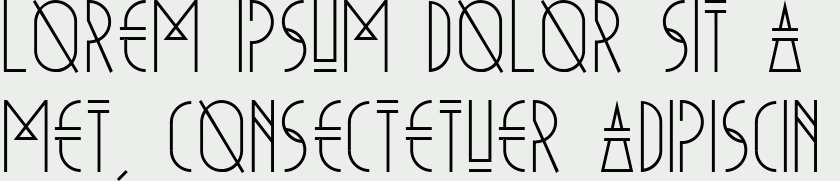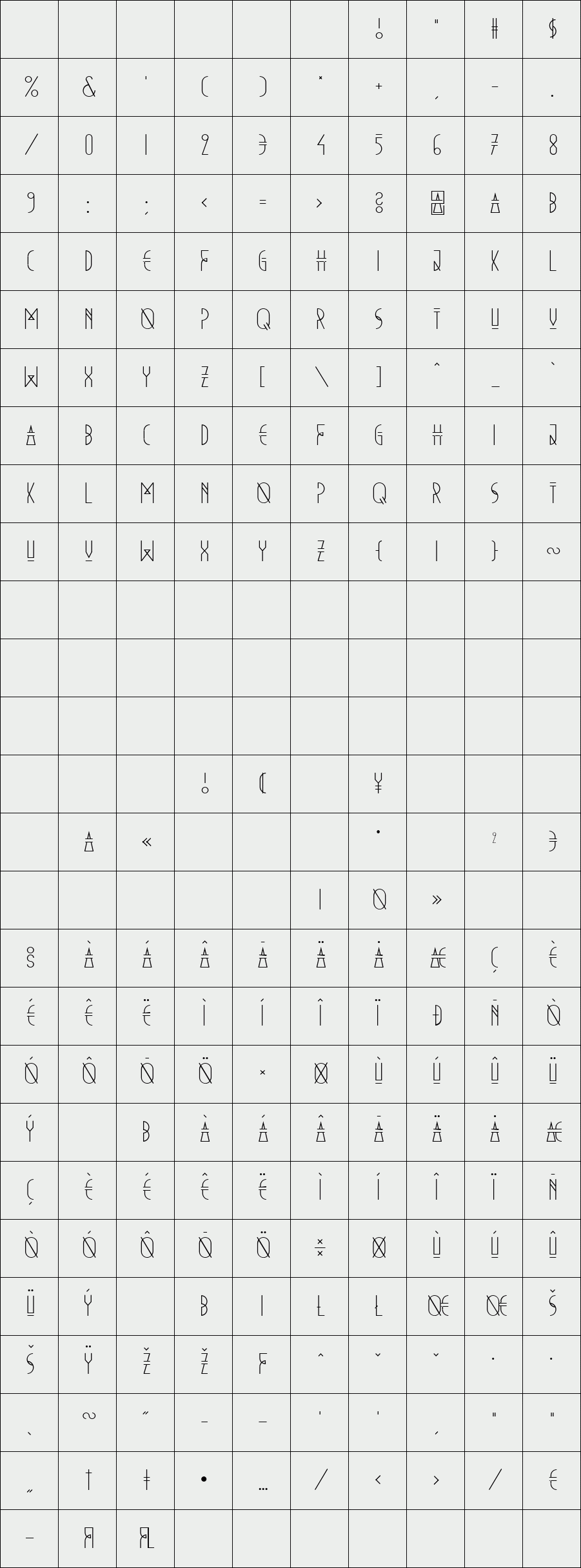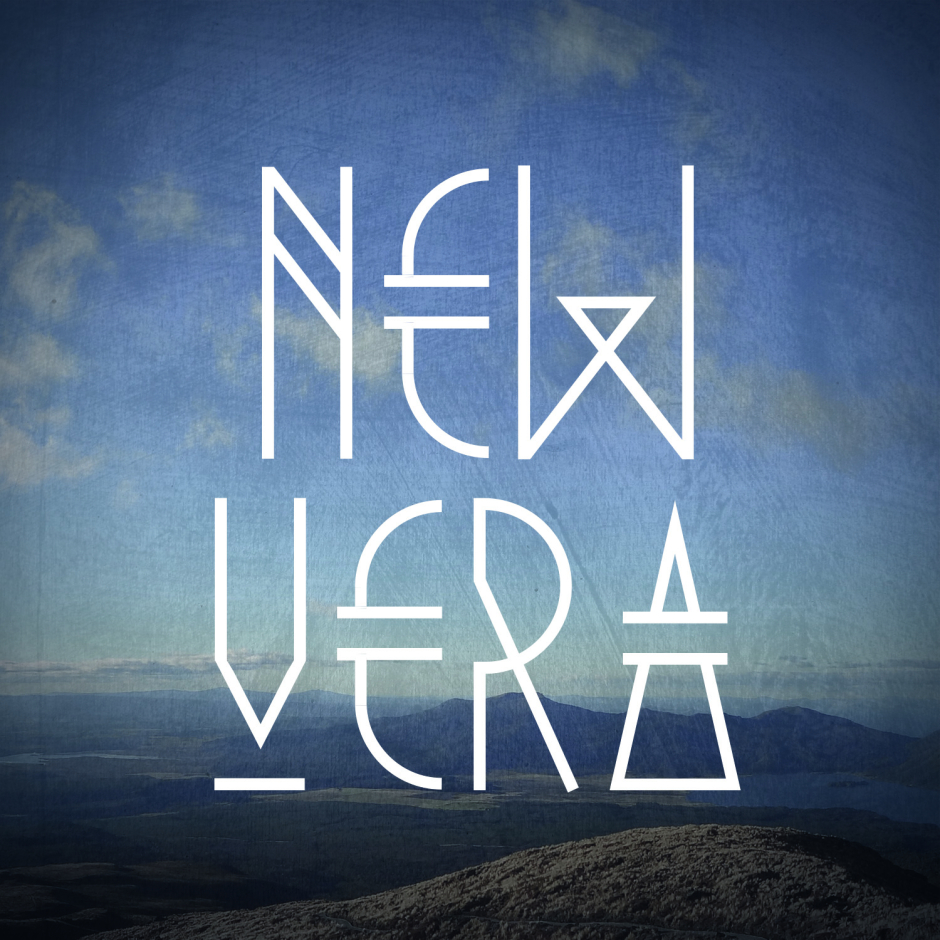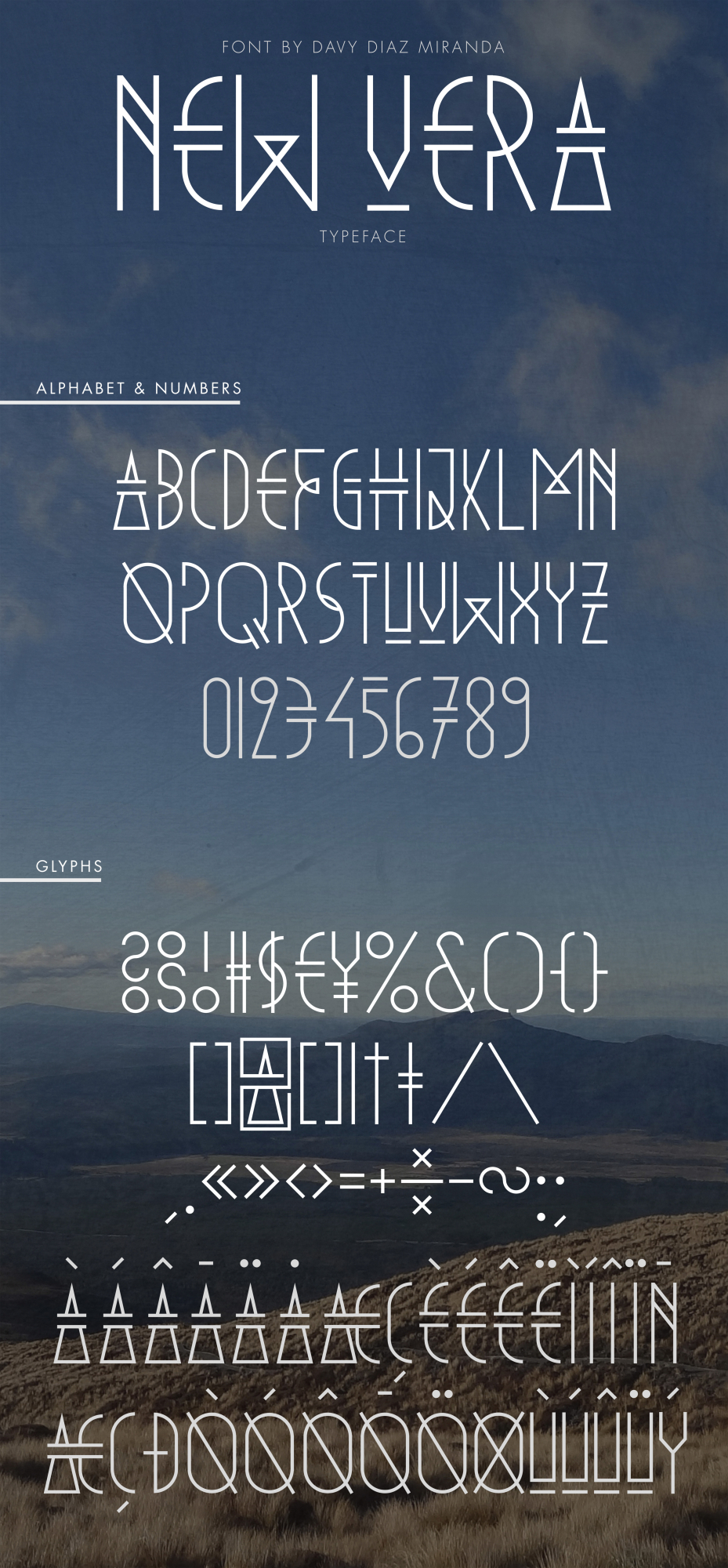
New Vera OpenType
Réalisation de la police «NEW VERA» inspirée par la police «Pyrénéés», réalisée par Mr.Zyan et d’Alice Nowak pour le site FONT YOU. L’allusion géographique est créée par ses formes et sa construction géométrique.
By Davy Diaz Miranda
Designer: Davy Diaz Miranda